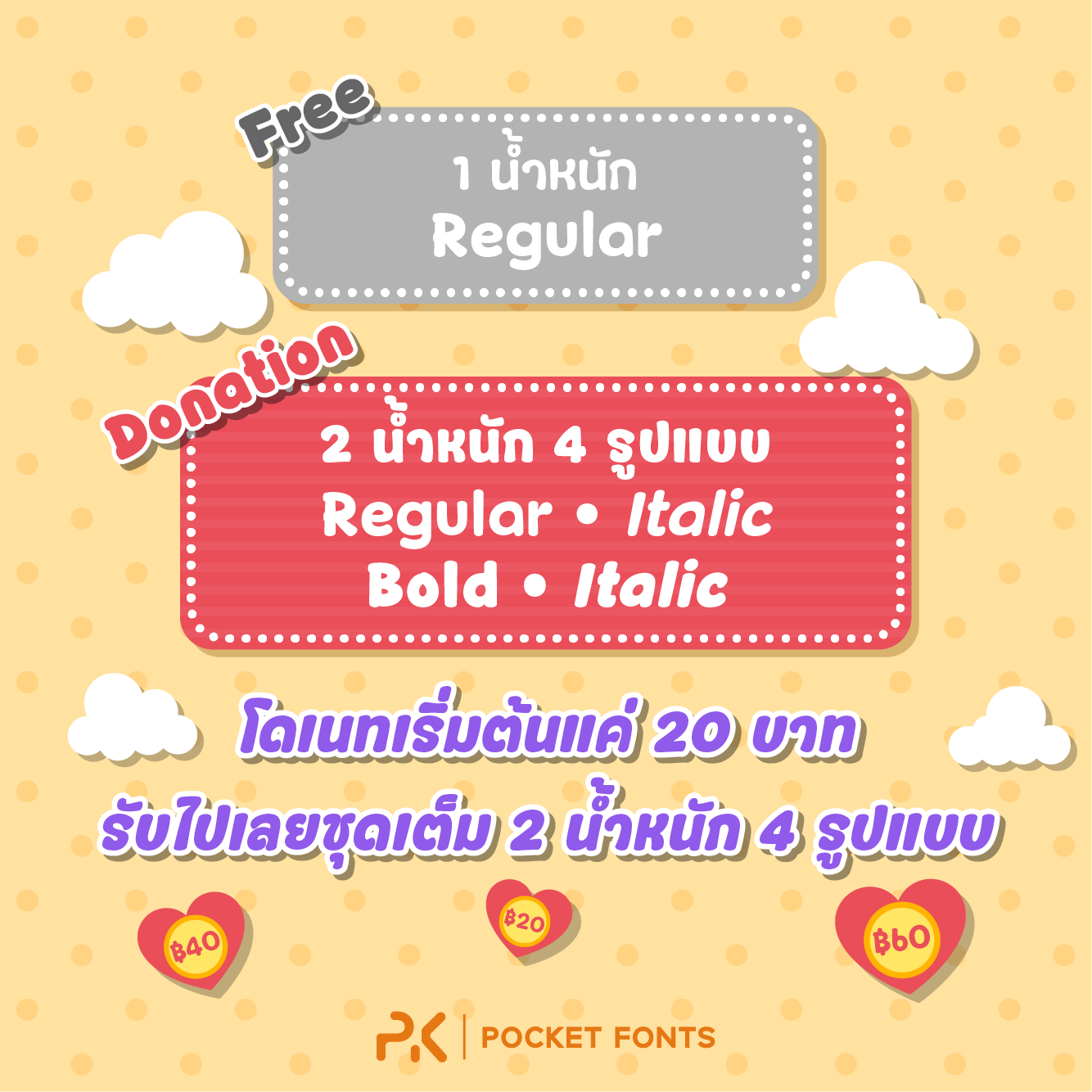
พีเค คริสต์มาส | PK Christmas
ชื่อฟอนต์ พีเค คริสต์มาส | PK Christmas
ฟอนต์ พีเค คริสมาสต์ ฟอนต์แนวน่ารักตัวปุ๊กลุก ที่จะช่วยเพิ่มความน่ารักอบอุ่นให้กับงานไหนก็ตามที่ฟอนต์นี้ไปอยู่(อวยเกิ๊น :28:) ฟอนต์นี้มี 2 น้ำหนัก 4 รูปแบบ แจกฟรี 1 น้ำหนัก และใช้ในเชิงพาณิชย์ได้ด้วย แต่ถ้า 1 น้ำหนักมันไม่เพียงพอก็สามารถสนับสนุนเลี้ยงน้ำเลี้ยงขนมพวกเราได้เริ่มต้น แค่ 20 บาทเท่านั้น เมื่อสนับสนุนแล้ว คุณจะได้ฟอนต์ชุดเต็ม 2 น้ำหนัก 4 รูปแบบ ไปเลยยย.